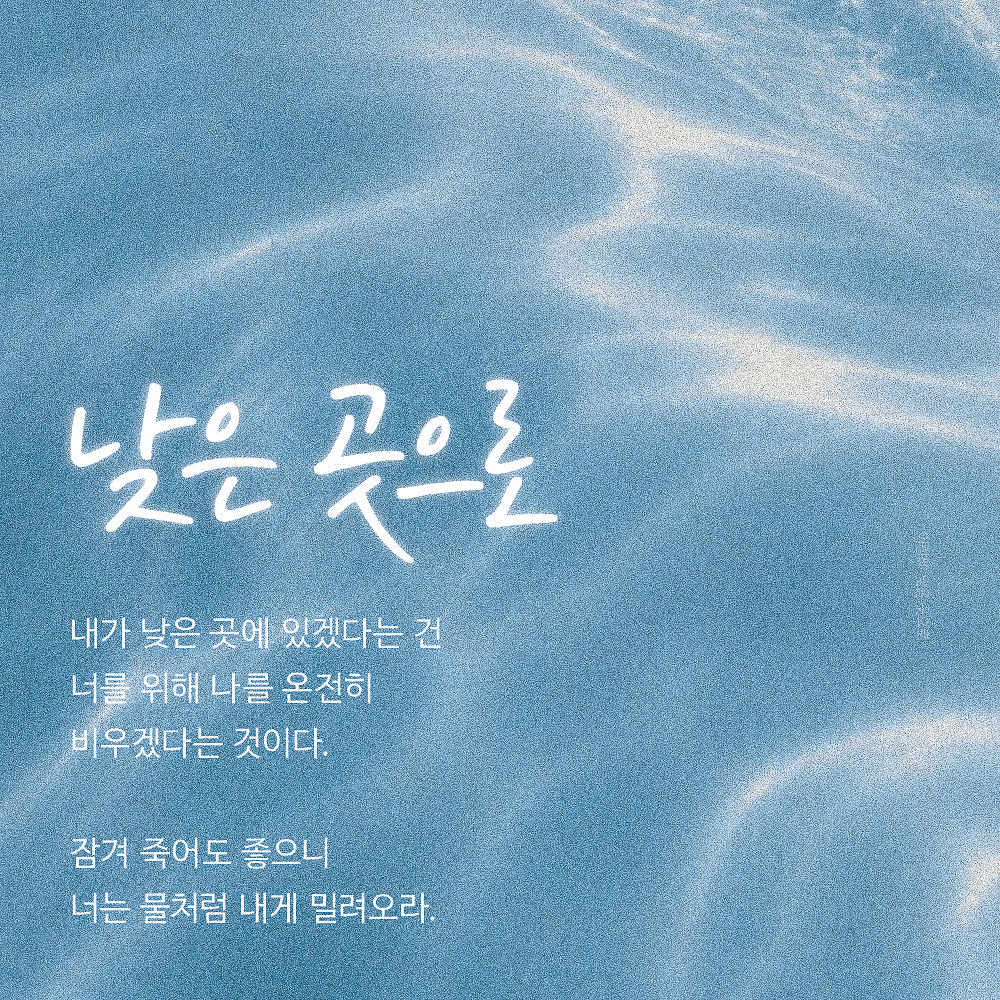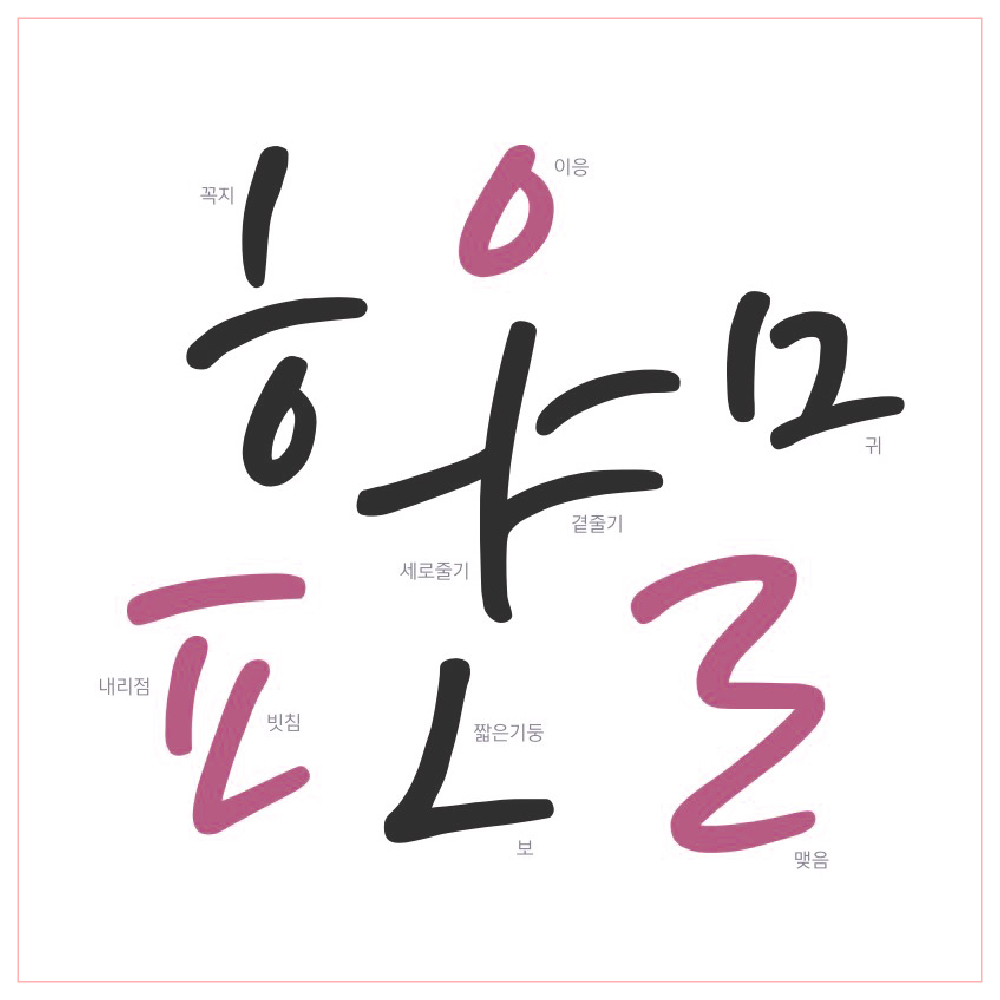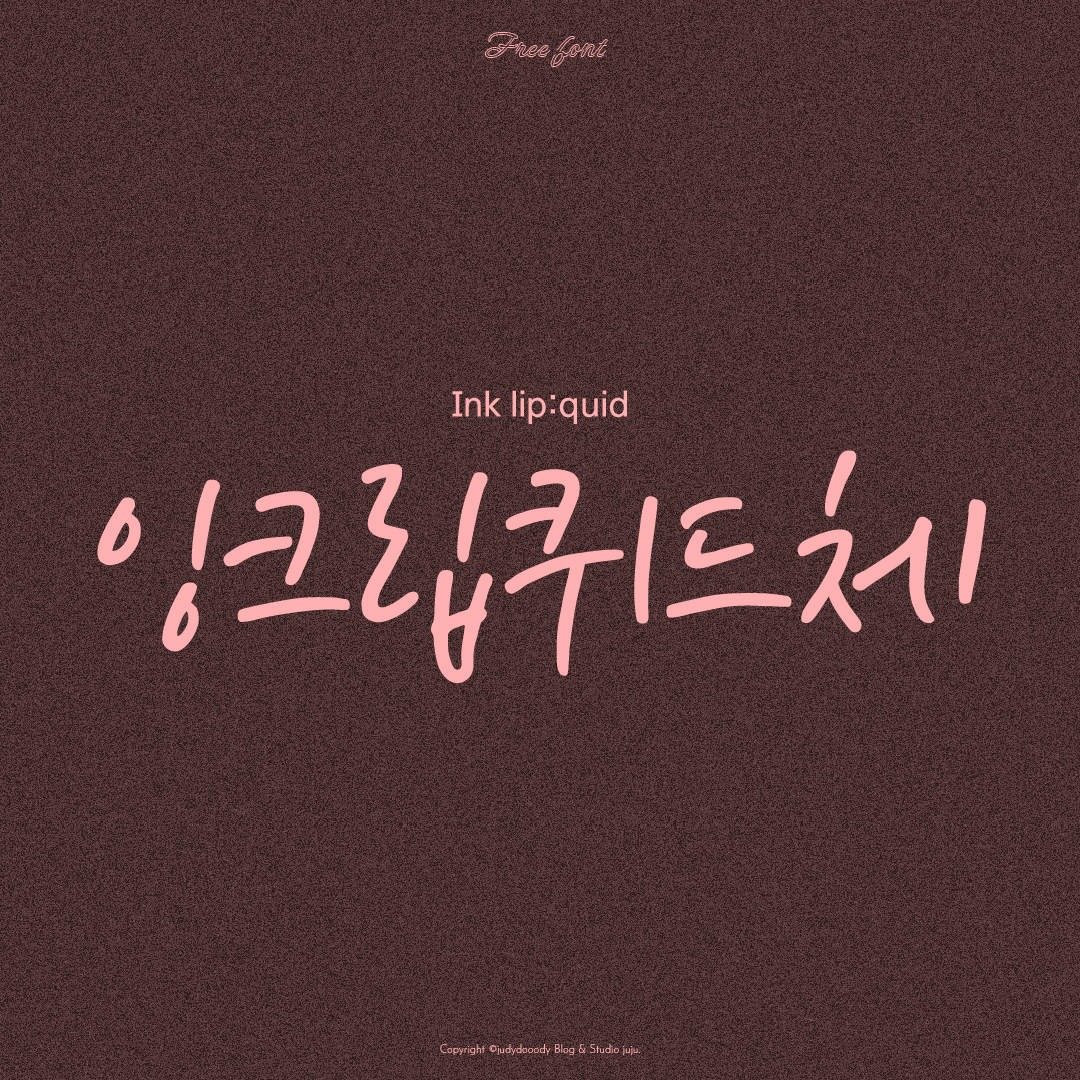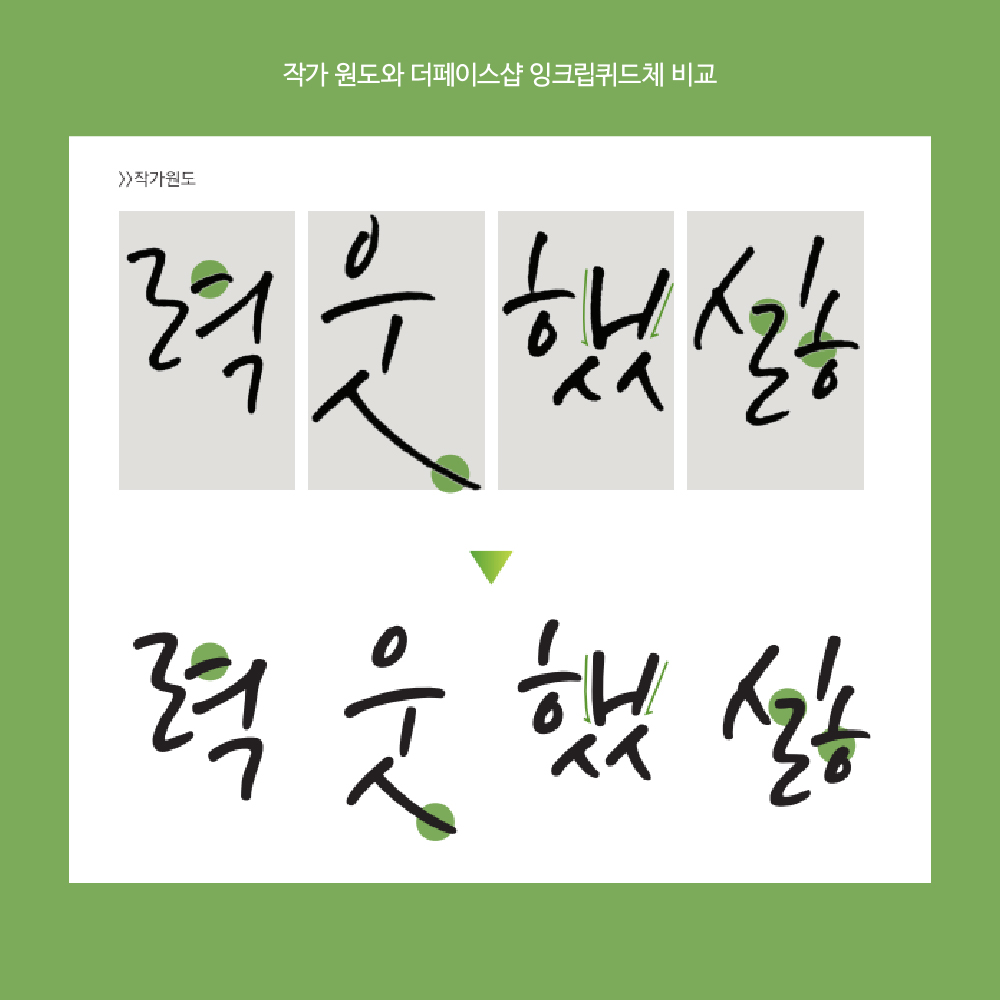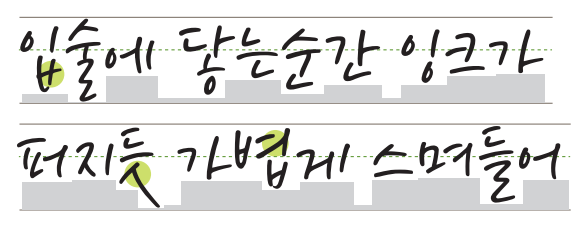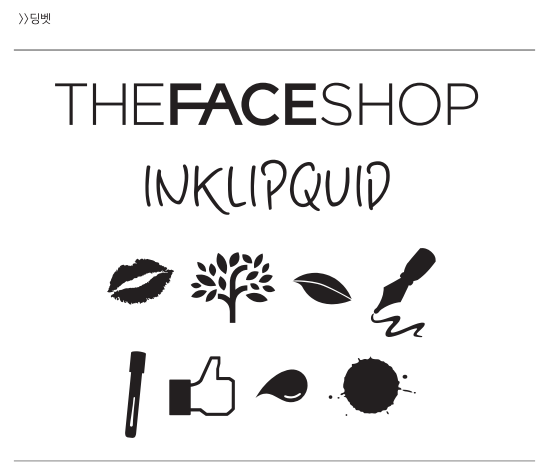
더페이스샵 잉크립퀴드체 소개 썸네일
더페이스샵 잉크립퀴드체는
최근에 나온 서체는 아니고
예전에 출시된 서체인데요.
저는 필기체가 필요할 때
산돌(Sandoll)의 공병각필, 공병각펜과 함께
더페이스샵 잉크립퀴드체를 주로 사용해요.
유연하게 잉크가 퍼지듯
자연스럽게 이어지는 느낌이 특징이에요.
실제 손글씨 특징이 잘 담겨 있어서
손으로 직접 쓴 듯한 느낌이 필요할 때
활용하기 좋은 서체예요
작가 원도와 잉크립퀴드체 비교 설명
출처 : 더페이스샵 잉크립퀴드체 typeface Guideline
이번에 공유하려고 찾아보다가 알게 됐는데
‘사공혜지’라는 작가님의 필체를 바탕으로
만든 폰트라고 하더라고요
작가님이 직접 쓴 손글씨의 느낌을
최대한 살려 제작했다고 해요.
그래서인지 폰트인데도 정형화된 느낌이 덜하고
진짜 손글씨 특유의 맛이 느껴지는
더페이스샵 잉크립퀴드체예요.ᐟ
스크립트 Script
손글씨 Handwritten
더페이스샵 잉크립퀴드체 서체 특징 설명
더페이스샵 잉크립퀴드체는
스크립트 1종으로 구성되어 있습니다
잉크립퀴드체 한글 서체 특징 설명
출처 : 더페이스샵 잉크립퀴드체 typeface Guideline
폰트 사용 예시
저도 공유하려 다시 찾아보게 된 계기가요즘 네이버 블로그에서 블로거들을 소개하는 팝업이 뜨는데
산돌(Sandoll)의 공병각펜을 사용하셔서
더페이스샵 잉크립퀴드체를 소개해드려야겠다 생각났어요 .ᐟ
산돌 공병각펜과 비교 설명
네이버 블로그 '블로그 있어요' 비교
더페이스샵 잉크립퀴드체도 어디에도 잘 어울리고
고딕과 함께 쓰면 잘 붙고 예쁘더라고요!
더페이스샵 잉크립퀴드체 활용방법
이정하 시인 '낮은 곳으로'